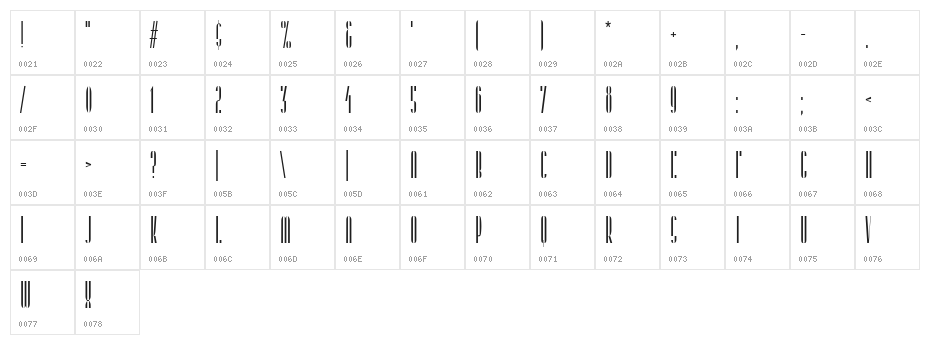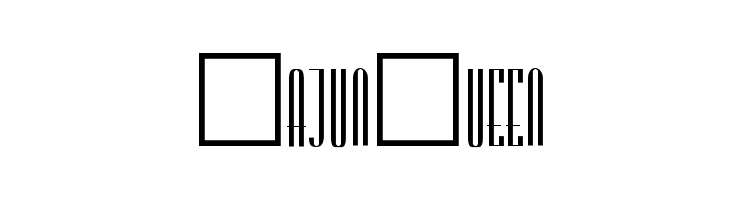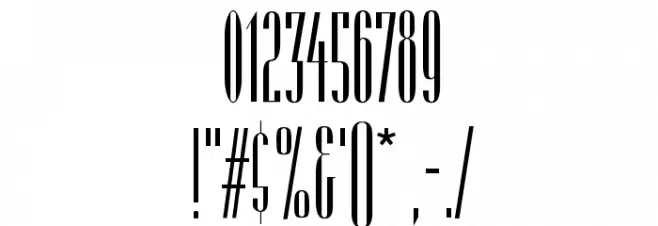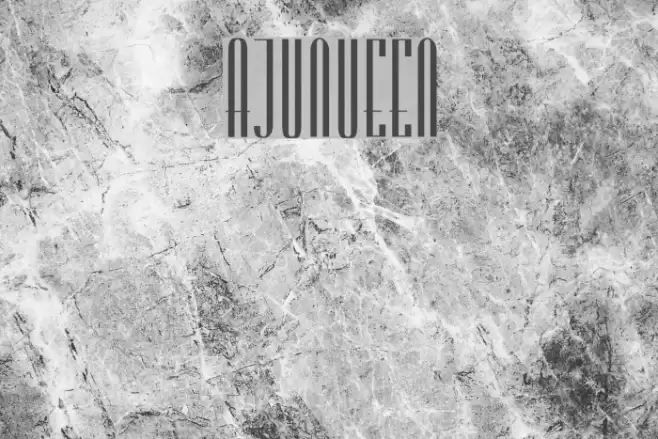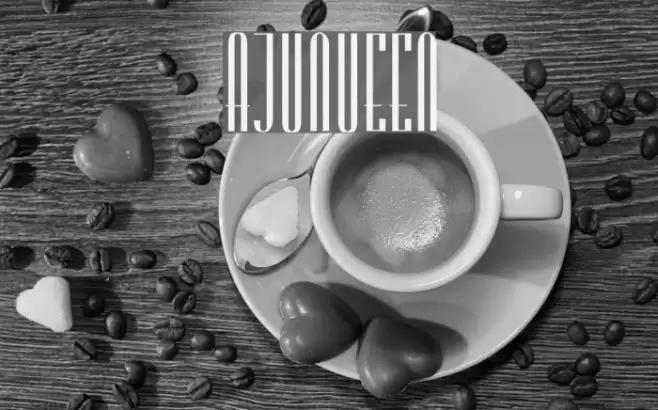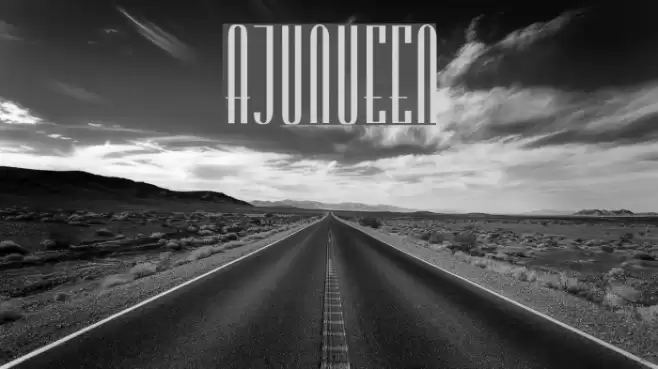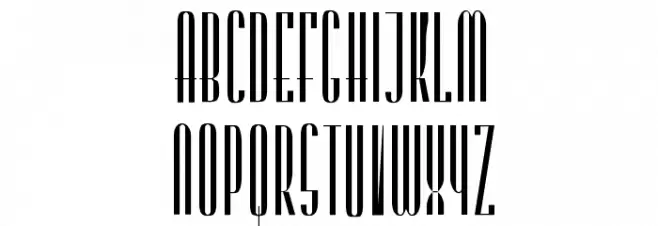
CajunQueen Font
| Stile generale | Modern, Elegant |
| Progetti proposti | Ideal for luxury branding, fashion magazines, high-end product packaging, and elegant event invitations. |